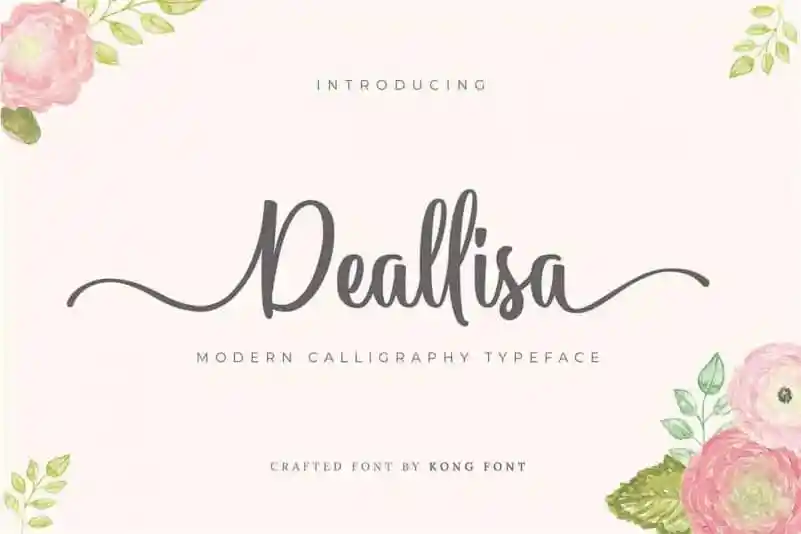
Deallisa Script Font – Download Grátis
Descubra Deallisa Script Font, uma fonte de script que irá revolucionar seu design. Desenvolvida pelo designer fontkong, esta fonte é perfeita para diversas finalidades, desde a criação de marcas e design interno até o título de livros ou até mesmo em embalagens ou anúncios. Seu estilo moderno contrasta com sua elegância antiquada, criando um visual único e envolvente. Grande parte do seu poder reside na linguagem suportada que vem com a fonte, tornando-a uma escolha perfeita para qualquer projeto, seja ele digital ou em impressão. Seja você uma marca de sucesso buscando renovar sua identidade visual, um designer de design interno desejando trazer elementos únicos ao seu trabalho, ou até mesmo um artesão que precisa criar embalagens atraentes para seus produtos, Deallisa Script Font tem o potencial de torná-lo destaque. Numa categoria repleta de fontes de script, esta é uma opção que merece ser revisitada sempre que você estiver buscando algo mais bonito e atemporal.